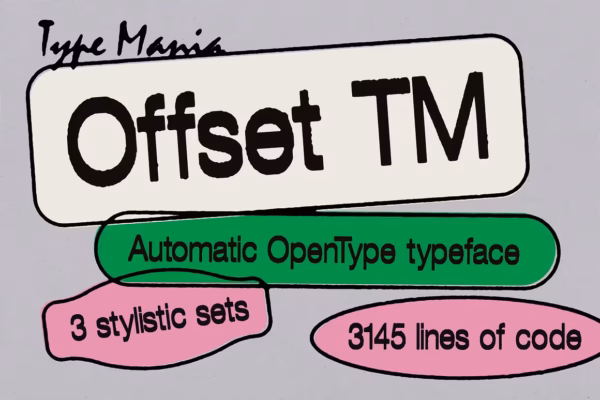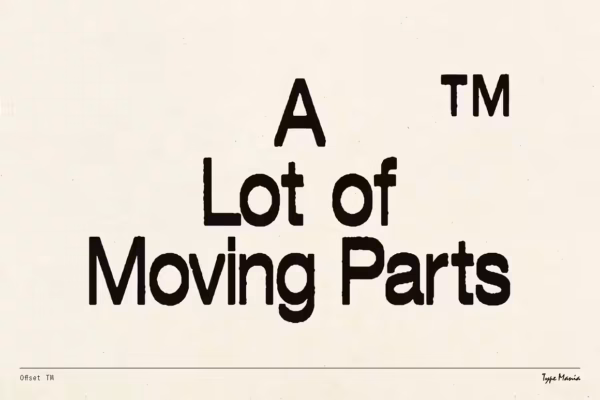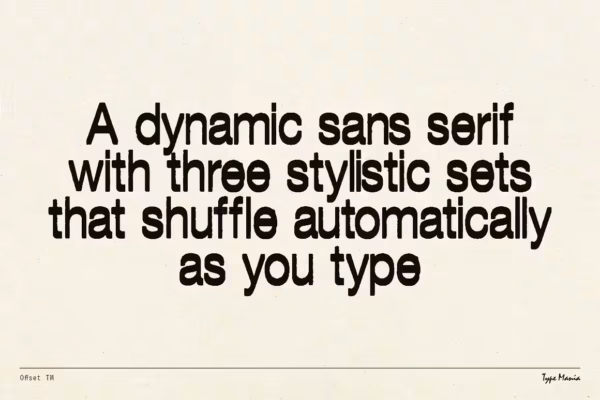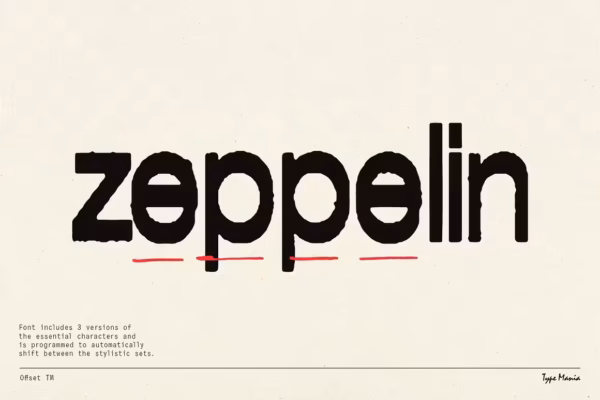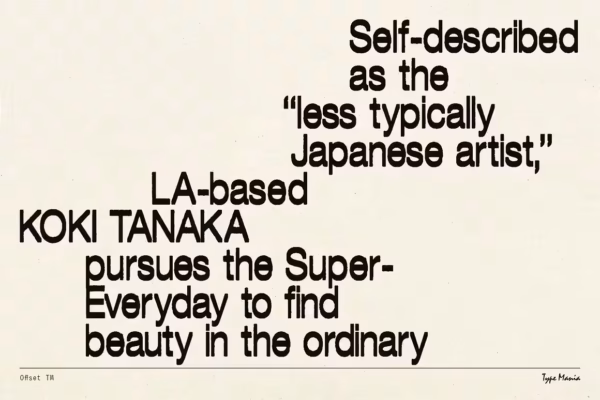
فونت Offset TM یک تایپ فیس پویا با 3145 خط کدنویسی است که ظاهر خشن و بافتدار را با ویژگیهای طراحی نوآورانه ترکیب میکند. این فونت نمایشی فقط ظاهر چشمنوازی ندارد، بلکه به دو مجموعه استایل مجهز است که بهصورت خودکار بین آنها جابهجا میشود. این قابلیت باعث میشود حروف تنوع بیشتری داشته باشند و بدون نیاز به تنظیمات اضافی، طرحهای شما طبیعیتر، جذابتر و منحصربهفرد به نظر برسند.
ویژگیهای OpenType:
- شامل 2 مجموعه استایل
- جابهجایی خودکار بین استایلها برای ایجاد تنوع در حروف و بخشیدن جلوهای طبیعی و منحصربهفرد به طراحی، بدون نیاز به تغییر دستی
زبانهای پشتیبانیشده:
- لاتین پایه
- کاراکترهای یورو
- 443 گلیف (Glyph)